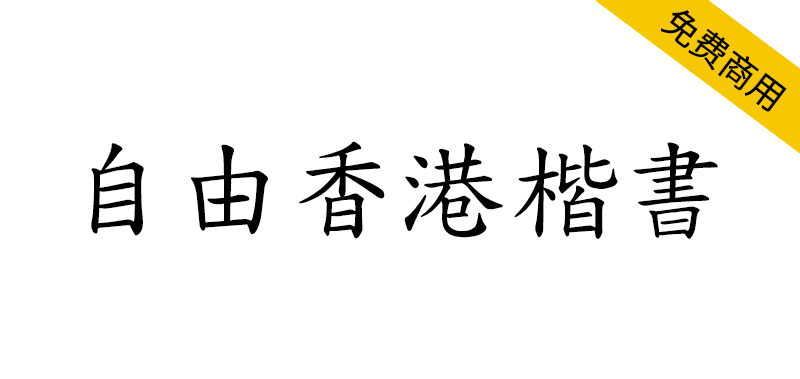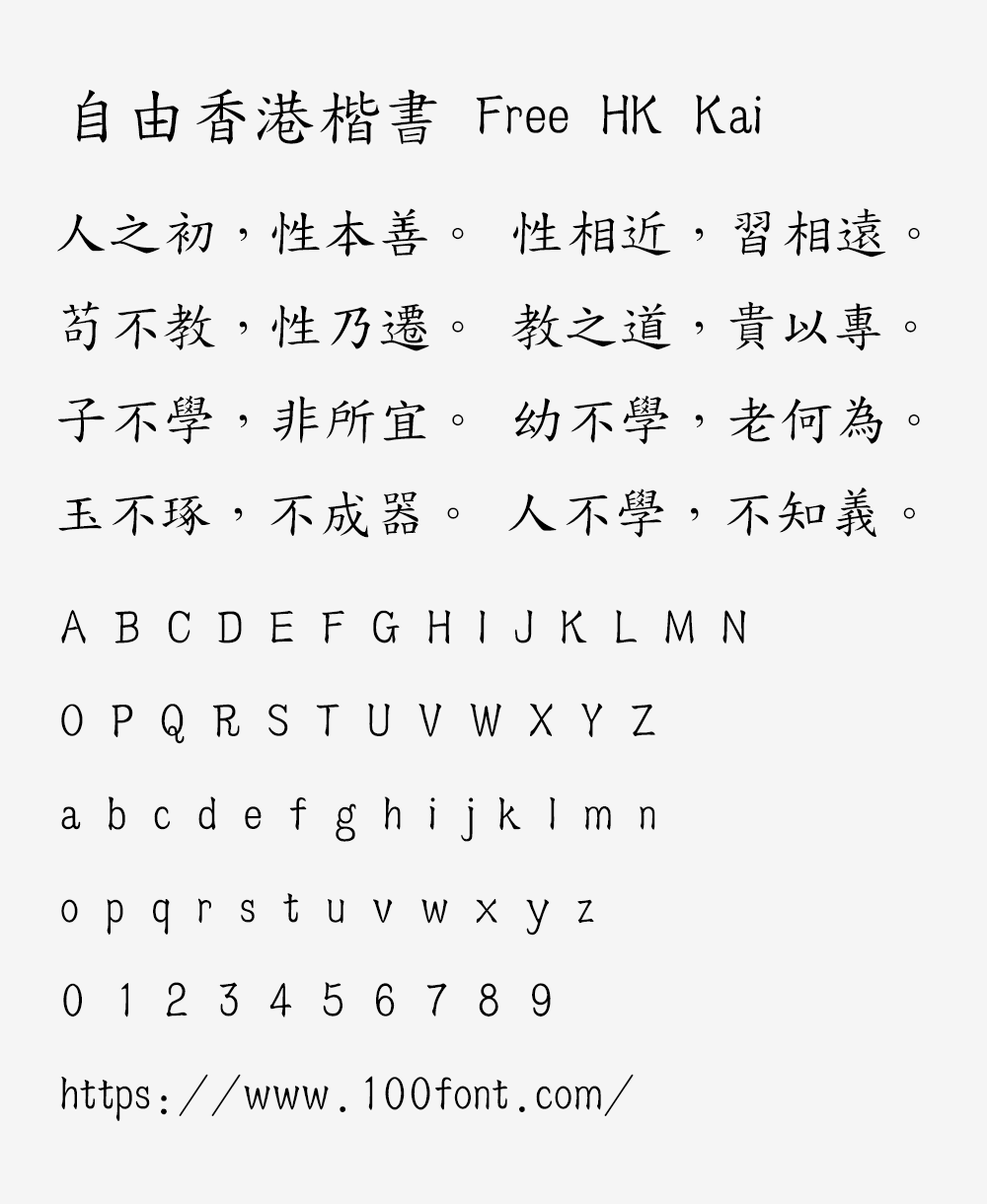
自由香港楷书(Free HK Kai)是由一群香港长者启动的开源项目。以香港人造香港字为口号,推动跨世代与跨界别的合作。依据香港教育局《香港小学学习字词表》2007年版的书写要求及修改台湾全字库楷体而成。现时版本完成字词表内4762字。而我们的目标是完成两万字,所以很需要你的支持和参与,欢迎联络团队,凝聚力量,继续开发。
字体标准来源:1、自由香港楷书(Free HK Kai)(下称本字型)是根据香港特别行区教育局课程发展处中国语文教育组于2012年所编制出版的《常用字字形表(2007年重排本)》为楷书字型基础作出修改。、本字型为「自由香港楷书」4700字版,根据《常用字字形表(2007年重排本)》共有4,762个小学生常用字。3、本字型修改来源于台湾全字库正楷体(中华民国行政院国家发展委员会,CNS11643中文标准交换码全字库网站,http://www.cns11643.gov.tw)。